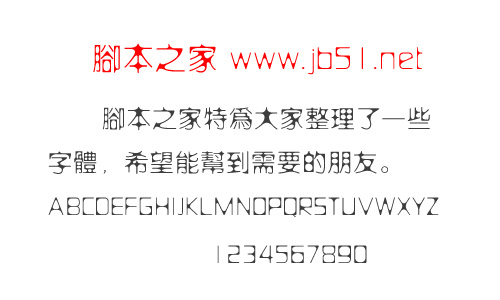
方正細(xì)珊瑚繁體字體是方正字體庫中的一種字體,方正細(xì)珊瑚的設(shè)計以細(xì)圓體為基礎(chǔ),字形結(jié)構(gòu)方正,筆畫圓潤且粗細(xì)均勻。這款字體最大的特征是筆畫交叉處的內(nèi)側(cè)添加了圓角,彼此相融,似珊瑚生長的形態(tài)。方正細(xì)珊瑚的風(fēng)格朦朧柔美,讓人感覺輕松休閑,適用于品牌廣告和產(chǎn)品包裝的設(shè)計。喜歡的朋友們可以前來下載使用。